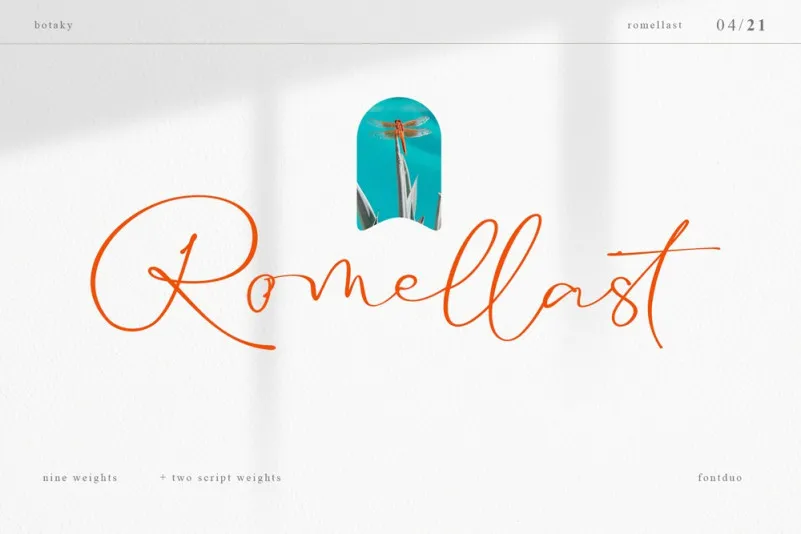
Romellast Font – Download Grátis
Romellast é uma fonte script casual que captura a energia das redes sociais mais recentes. Seu traço contrasta alto e seu design dos caracteres é limpo e descontraído, criando um estilo fresco e alegre. A inspiração para o design vem do uso de ferramentas de Instagram Stories, onde as pessoas não necessariamente são designers, mas usam essa ferramenta para criar histórias divertidas e únicas. Romellast também inclui uma ligatura alternativa que parece natural e não é estilizada em excesso, oferecendo um toque ainda mais autêntico aos teus design. Ainda mais interessante, a fonte Romellast vem em dois estilos: um fino e um regular. O estilo fino é menos espesso, ideal para aplicar em textos de leitura, enquanto o estilo regular oferece uma opção mais forte e robusta. Essas alternativas permitem que você escolha a melhor opção dependendo do seu projeto ou da sua preferência pessoal. Com Romellast, deixe-se levar pelo espírito leve e descolado da fonte que se destaca perfeitamente tanto no design de logotipos quanto em títulos de aplicativos e materiais digitais.